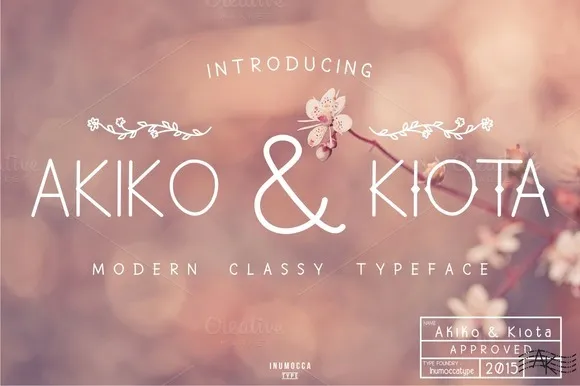
A Akiko & Kiota é uma elegante e moderna fonte display, perfeita para quem busca uma opção única que se destaca em qualquer projeto visual. Suas linhas clean e minimalistas não apenas reforçam a identidade do seu produto ou marca, mas também dão um toque vintage à sua logomarca e materiais promocionais. Com ela, você pode criar identidades visuais memoráveis para suas embalagens de catálogo, selos de eventos e até mesmo cartazes e cartões de visita personalizados. A Akiko & Kiota é uma escolha ideal não só para logotipos e materiais promocionais, mas também para usar em texturas de mídia social e outros elementos digitais que precisam ser chamativos e memoráveis. Seja qual for o seu próximo projeto visual, a Akiko & Kiota pode ajudar a destacá-lo na multidão.